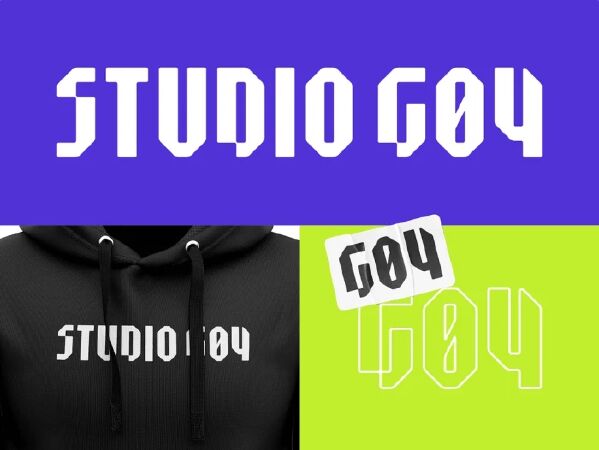
Top 9 trong Top 10 xu hướng font chữ hot nhất trong thiết kế đồ họa năm 2022.
kiểu chữ không phải lúc nào cũng có mục đích chính là dễ đọc trong vòng một giây. Một số thiết kế cho phép chúng tôi biểu đạt và thử nghiệm hơn một chút về các mẫu chữ mà chúng tôi đang sử dụng với tư cách là nhà thiết kế. Và với rất nhiều nhà thiết kế kiểu chữ đã tạo ra những kiểu chữ 'on-the-edge' đáng kinh ngạc cho phép chúng tôi làm việc với một phông chữ có thể cài đặt mà không cần phải tạo mọi thứ bằng tay. Hoàn toàn một trong những ưu điểm của phần mềm tạo phông chữ có thể truy cập được cho nhiều đối tượng hơn là số lượng lớn các tùy chọn có sẵn cho các kiểu thử nghiệm này.